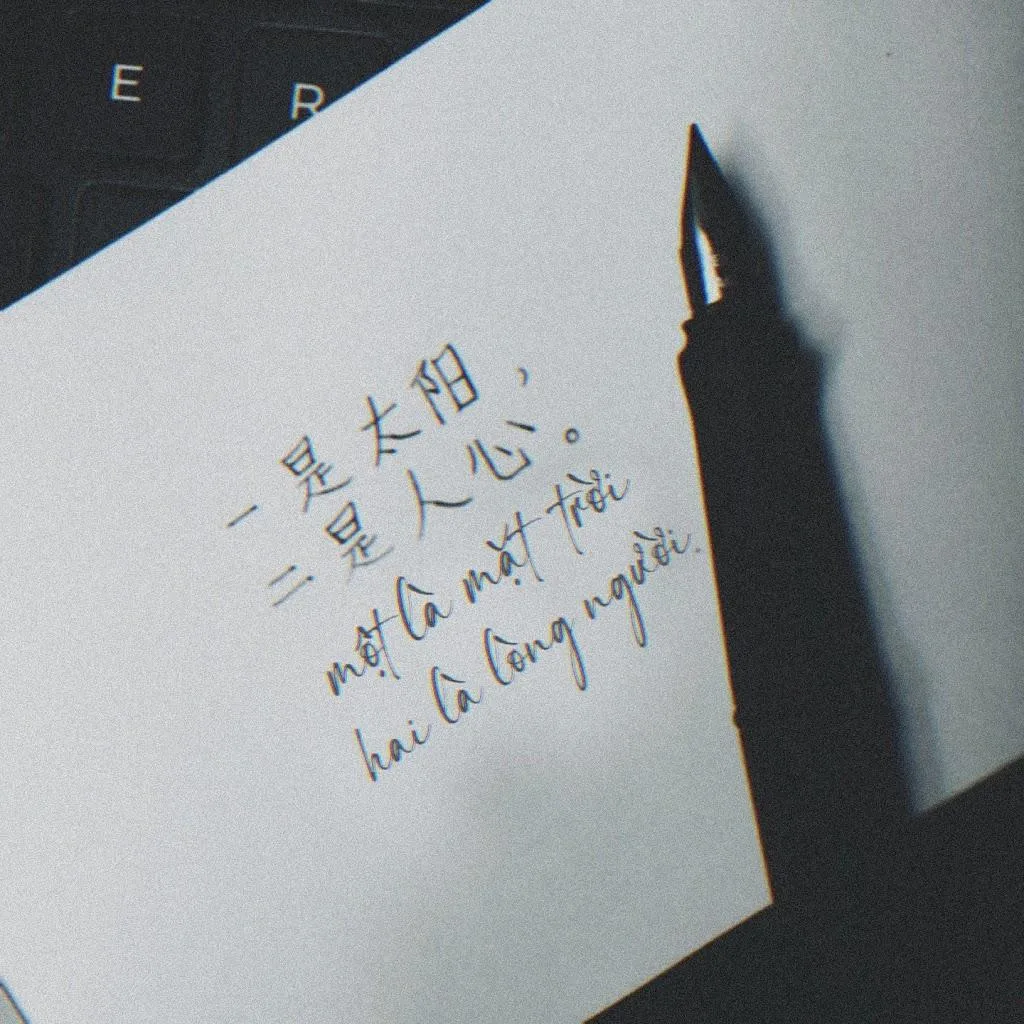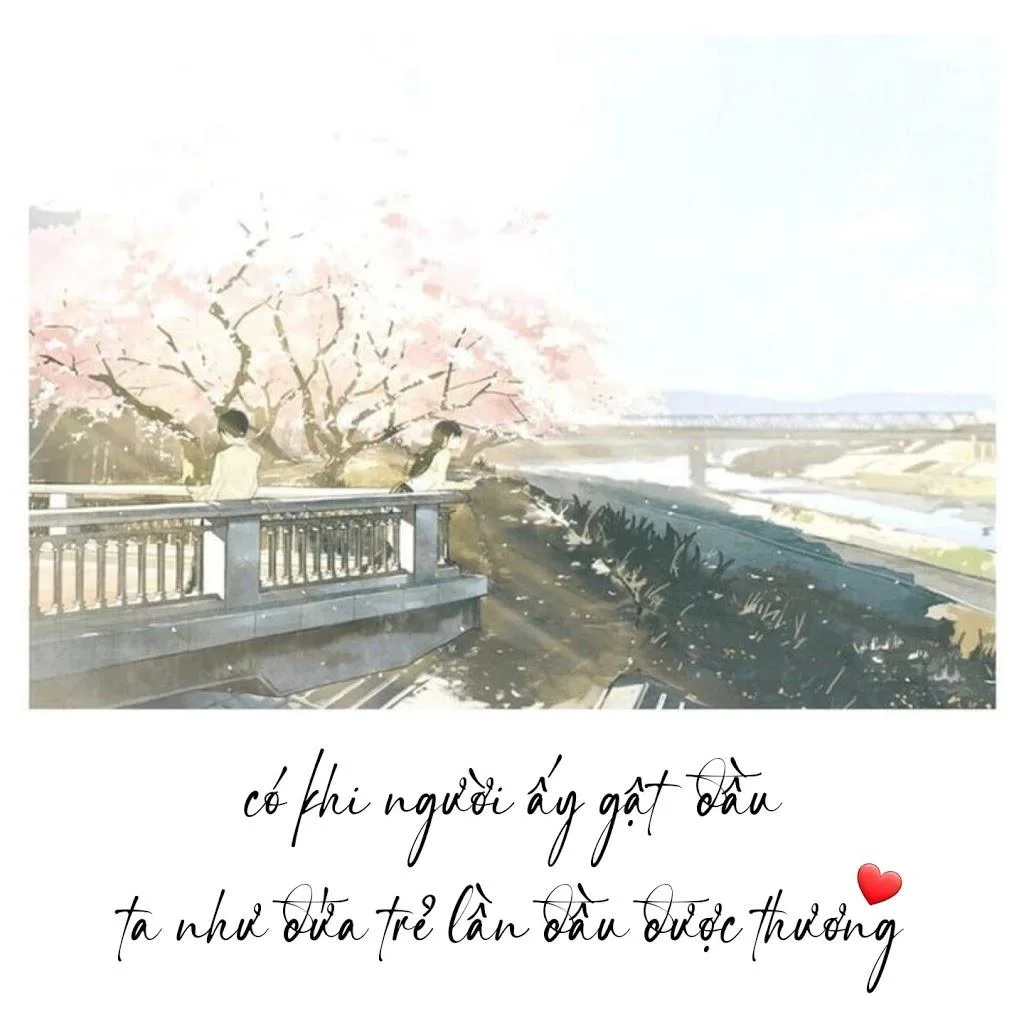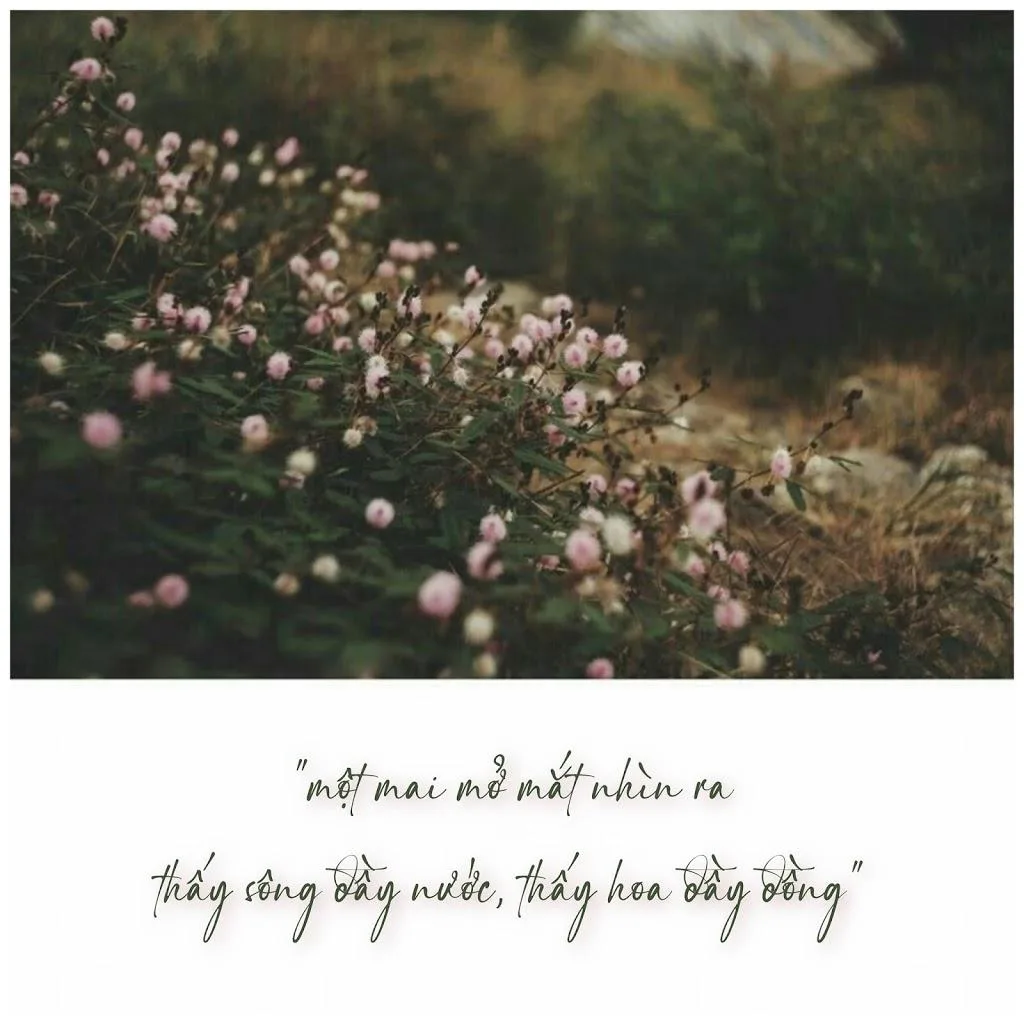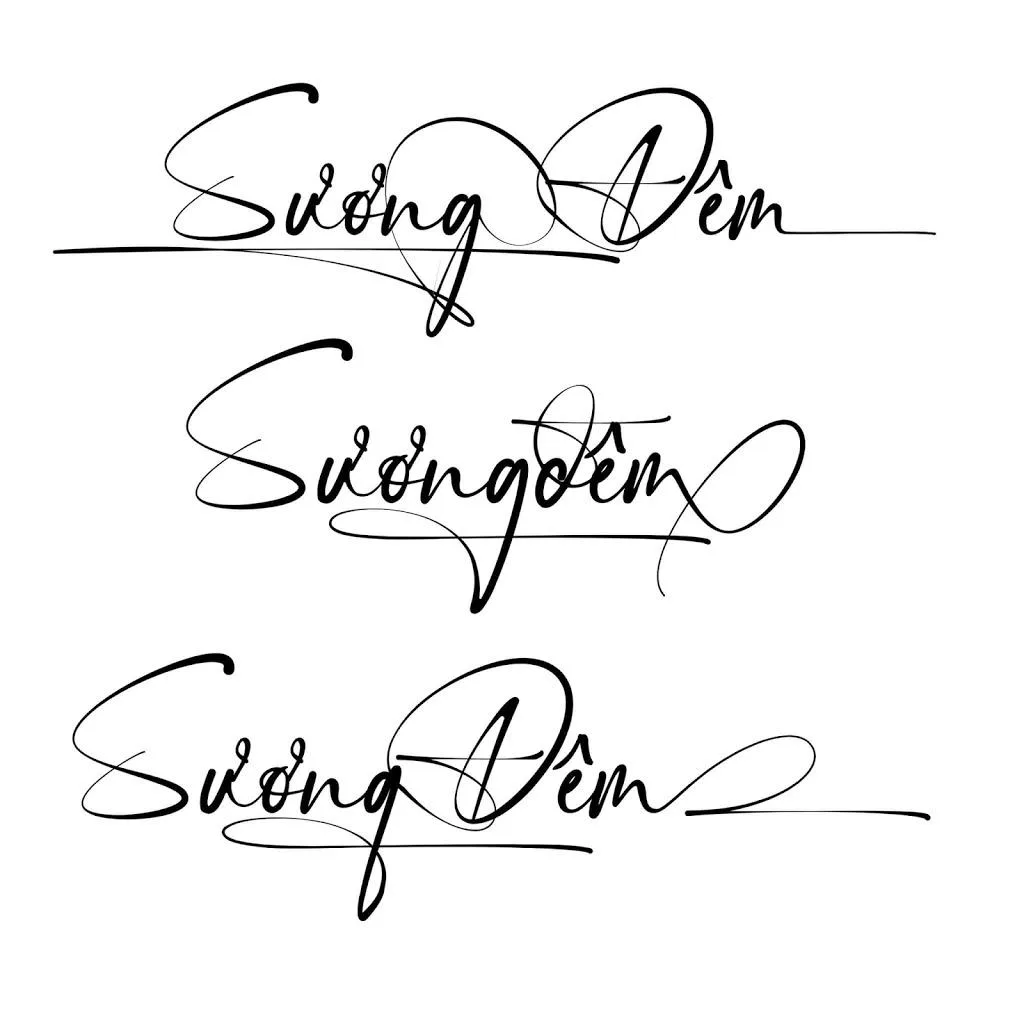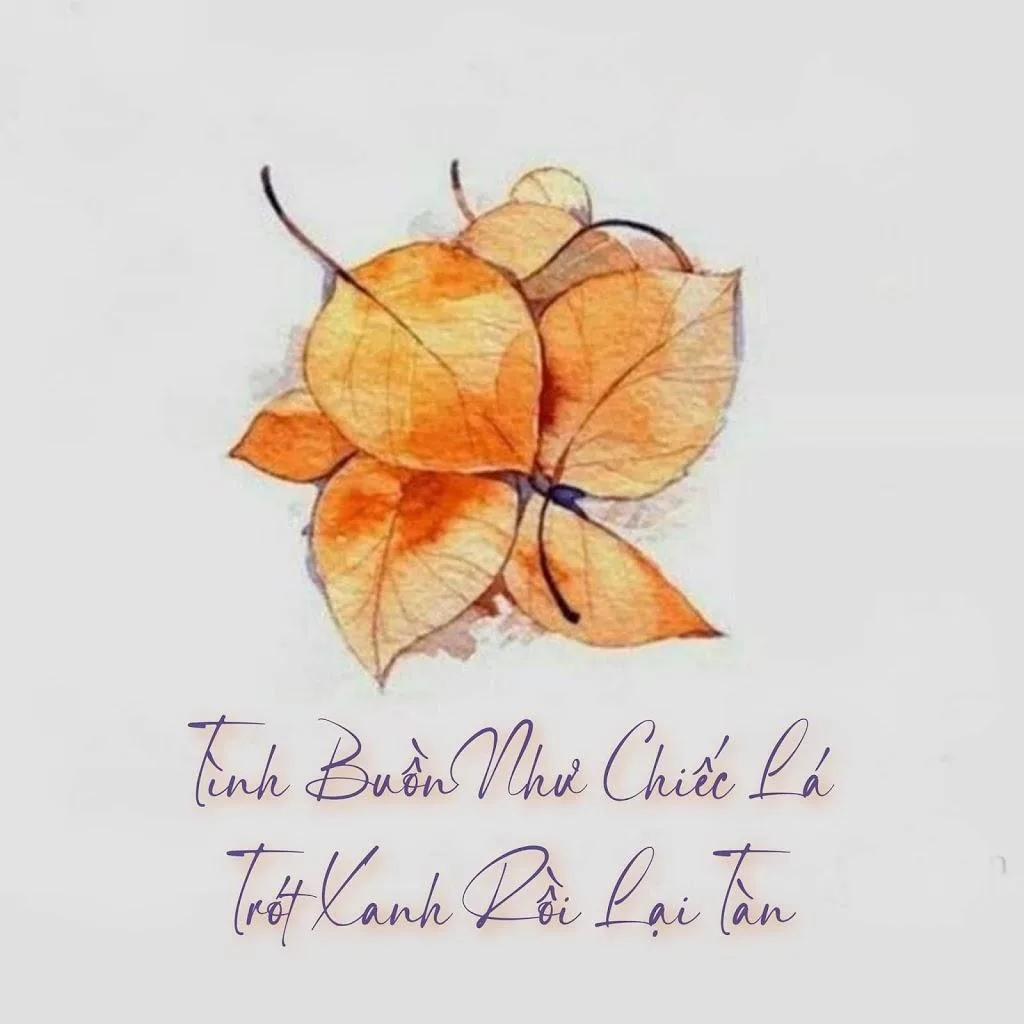
Test font chữ SignRathi V3
SignRathi là một font chữ ký Việt hóa được thiết kế bởi Dwi Ahidian và Việt hóa bởi Đức Thủy. Font này mô phỏng chữ viết tay một cách tự nhiên, với nhiều ký tự thay thế đẹp mắt, phù hợp cho nhiều mục đích thiết kế như logo, thiệp mời, quảng cáo, watermark, v.v. Phiên bản V2 3.2023 có nhiều cải tiến về quy tắc gõ và bộ ký tự. Font được cung cấp miễn phí cho mục đích cá nhân và phi thương mại.
Giới thiệu Font Chữ Ký SignRathi:
Font chữ ký Việt hóa SignRathi là một lựa chọn tuyệt vời cho những ai muốn tạo dấu ấn cá nhân hoặc thương hiệu thông qua chữ ký. Với nét chữ thanh thoát, tinh tế và khả năng tùy biến cao, SignRathi mang đến sự chuyên nghiệp và hiện đại cho bất kỳ dự án nào.
Các tính năng nổi bật của SignRathi V2 3.2023:
- Quy tắc gõ đơn giản: Giúp người dùng dễ dàng truy cập và sử dụng các ký tự đặc biệt trên cả máy tính và điện thoại. Ví dụ: gõ “a1”, “a2”, “a3″… để có các biến thể của chữ “a”; gõ “a0” để có chữ “a” gạch chân; gõ “A1”, “B1″… cho chữ in hoa.
- Bộ ký tự thay thế phong phú: Cung cấp nhiều kiểu chữ khác nhau, cho phép người dùng thỏa sức sáng tạo và tạo ra những chữ ký độc đáo.
- Ứng dụng đa dạng: Phù hợp cho thiết kế logo, thương hiệu, thiệp mời, văn phòng phẩm, bài đăng mạng xã hội, quảng cáo, bao bì sản phẩm, nhiếp ảnh, watermark và nhiều mục đích cá nhân khác như tạo chữ ký điện tử.
Hình ảnh demo font chữ ký SignRathi
Một số logo chữ ký được thiết kế từ font Fz SignRathi
Hướng dẫn sử dụng ký tự đẹp trong Sign Rathi
Font phù hợp để tạo chữ ký cá nhân cũng như sử dụng làm những typo mô phỏng chữ viết tay khá hữu ích. Font có 5 bộ ký tự thay thế mô phỏng theo dạng tốc ký cá nhân như gạch chân, nét móc, nét nối, nên bạn có thể thỏa sức sáng tạo với bộ font này.
Font SignRathi là một công cụ hữu ích cho việc tạo ra những chữ ký đẹp và chuyên nghiệp. Với hướng dẫn chi tiết và các mẹo được cung cấp, bạn có thể dễ dàng tận dụng tối đa tiềm năng của font chữ này.